Chuỗi ký tự “PGS.TS Nguyễn Văn A” dài 17 chữ, vượt ngưỡng 15 ký tự thường được xem là giới hạn an toàn cho thẩm mỹ trên ngực áo blouse. Câu hỏi đặt ra không phải là chọn font nào “đẹp” nhất, mà là làm sao để dòng chữ dài này giữ được bố cục chặt chẽ và sắc nét trên vải.
Nhiều người cho rằng việc chọn font thêu áo blouse chỉ là vấn đề cảm quan. Thực tế, đây là bài toán kỹ thuật cân bằng giữa cấu trúc ký tự và độ bền của mũi thêu. Khi chuỗi tên dài, font không phù hợp có thể khiến chữ bị vỡ bố cục hoặc mờ nhòe sau vài lần giặt. Với các học vị y tế nhiều chữ cái, font serif hoặc bold thường chiếm nhiều không gian ngang hơn do thân chữ dày và khoảng trắng giữa các ký tự rộng. Ngược lại, font sans-serif mảnh giúp nén các ký tự gần nhau hơn, giúp chuỗi dài vẫn giữ được sự trang trọng mà không làm phình to vùng thêu.
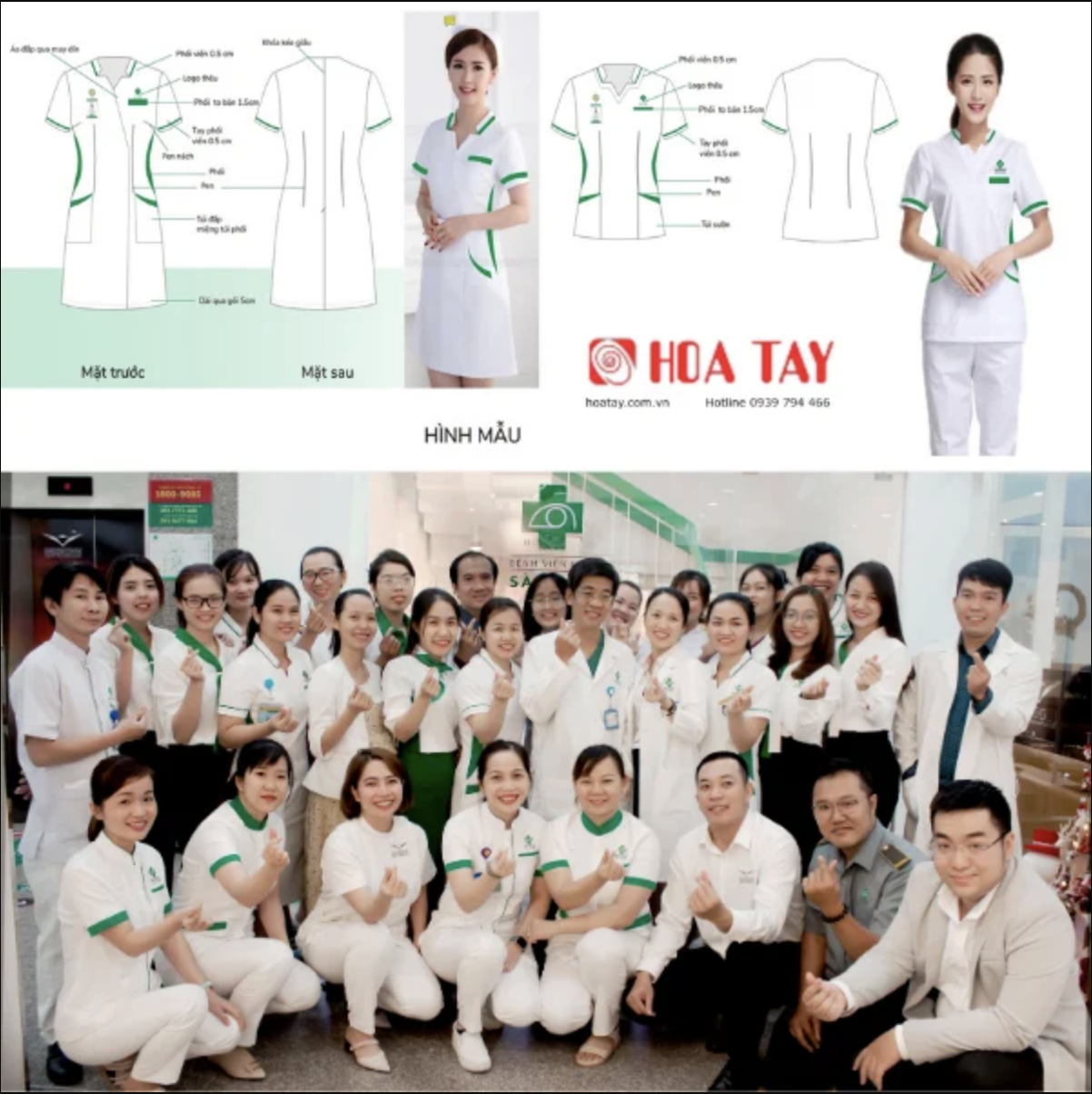
Nguyên tắc chung là chọn font có khoảng chữ hẹp (narrow tracking) và thân chữ mảnh (light weight) cho các chức danh dài. Cách tiếp cận này đảm bảo mỗi nét thêu có đủ diện tích vải để bám dính, tránh tình trạng chỉ bị căng đứt hoặc lem nhòe. Sự gọn gàng của font chữ chính là yếu tố then chốt giúp giữ nguyên tính chuyên nghiệp của bộ đồng phục y tế.
So sánh kỹ thuật thêu đồng phục giữa 3 nhóm font chữ
Khi đối mặt với các chuỗi ký tự dài như “PGS.TS” hay “BS.CKII”, việc lựa chọn font chữ là bài toán kỹ thuật trực tiếp. Mỗi nhóm font tương tác khác nhau với mũi chỉ và vải, ảnh hưởng đến độ rõ nét của chữ sau thời gian sử dụng.
Nhóm font in đậm và Serif
Nhóm này mang lại cảm giác trang trọng, phù hợp với không khí y tế. Tuy nhiên, thân chữ dày khiến chúng chiếm nhiều không gian ngang hơn. Khi áp dụng cho chức danh dài, mật độ mũi thêu phải dày hơn để đảm bảo độ phủ, dễ dẫn đến tình trạng các nét chữ bị lem nhòe. Nếu kích thước chữ bị thu nhỏ, các chân serif mảnh sẽ dễ bị đứt gãy hoặc biến dạng trong quá trình vận hành máy.
Giới hạn của font viết tay
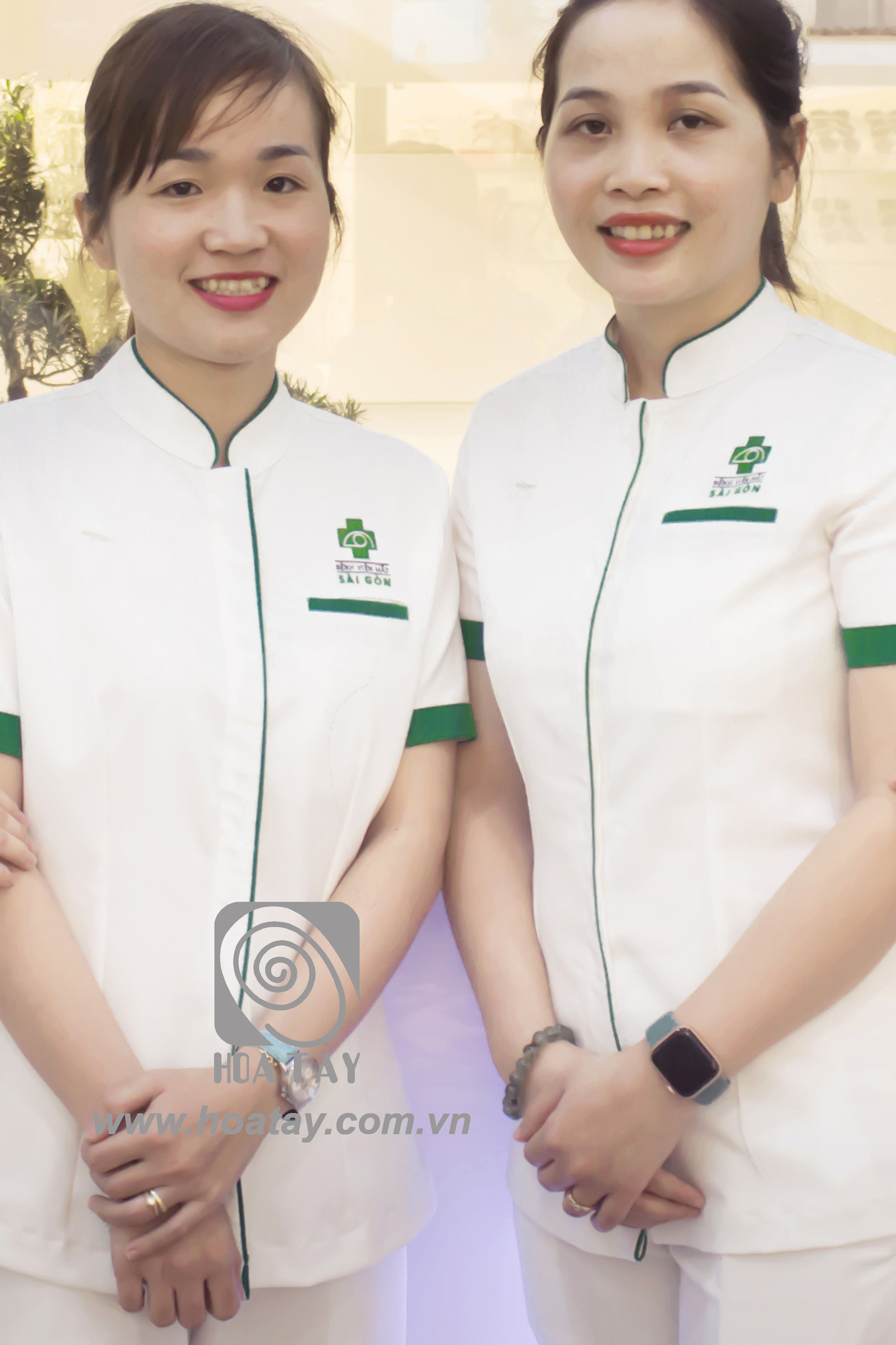
Font viết tay (calligraphic) tạo vẻ mềm mại và nghệ thuật, phù hợp cho tên ngắn. Tuy nhiên, khi thêu tên y bác sĩ có học vị dài, các nét uốn lượn tạo ra nhiều điểm chuyển hướng cho kim thêu. Điều này đòi hỏi tay nghề cao để tránh chỉ bị đứt đoạn. Với chuỗi ký tự dài, font viết tay thường tạo cảm giác rối rắm và khó đọc từ xa, làm giảm tính chuyên nghiệp trong môi trường bệnh viện.
Giải pháp tối ưu: Sans-serif medium weight
Nhóm font không chân (sans-serif) với độ dày vừa phải (medium weight) được xem là lựa chọn an toàn nhất. Chúng cân bằng tốt giữa tính hiện đại và độ bền. Cấu trúc ký tự thẳng và đồng đều giúp máy thêu duy trì mật độ mũi ổn định, tránh hiện tượng phồng vải. Font sans-serif medium weight giúp chữ thêu sắc nét, dễ đọc ngay cả ở kích thước nhỏ, đồng thời giữ được sự trang trọng mà không quá nặng nề như font serif.
Vị trí thêu tên y bác sĩ: nguyên tắc không che bảng tên
Xác định đúng vị trí là bước quyết định để bộ đồng phục vừa đạt thẩm mỹ vừa không cản trở công việc. Quy tắc chung trong kỹ thuật thêu đồng phục là đặt chuỗi ký tự ở ngực trái hoặc tay áo trái. Yếu tố then chốt là chữ thêu không được chồng lấp lên logo bệnh viện hay vị trí gắn bảng tên. Điều này giúp người bệnh dễ dàng nhận diện nhân viên mà không cần tách bảng tên ra.
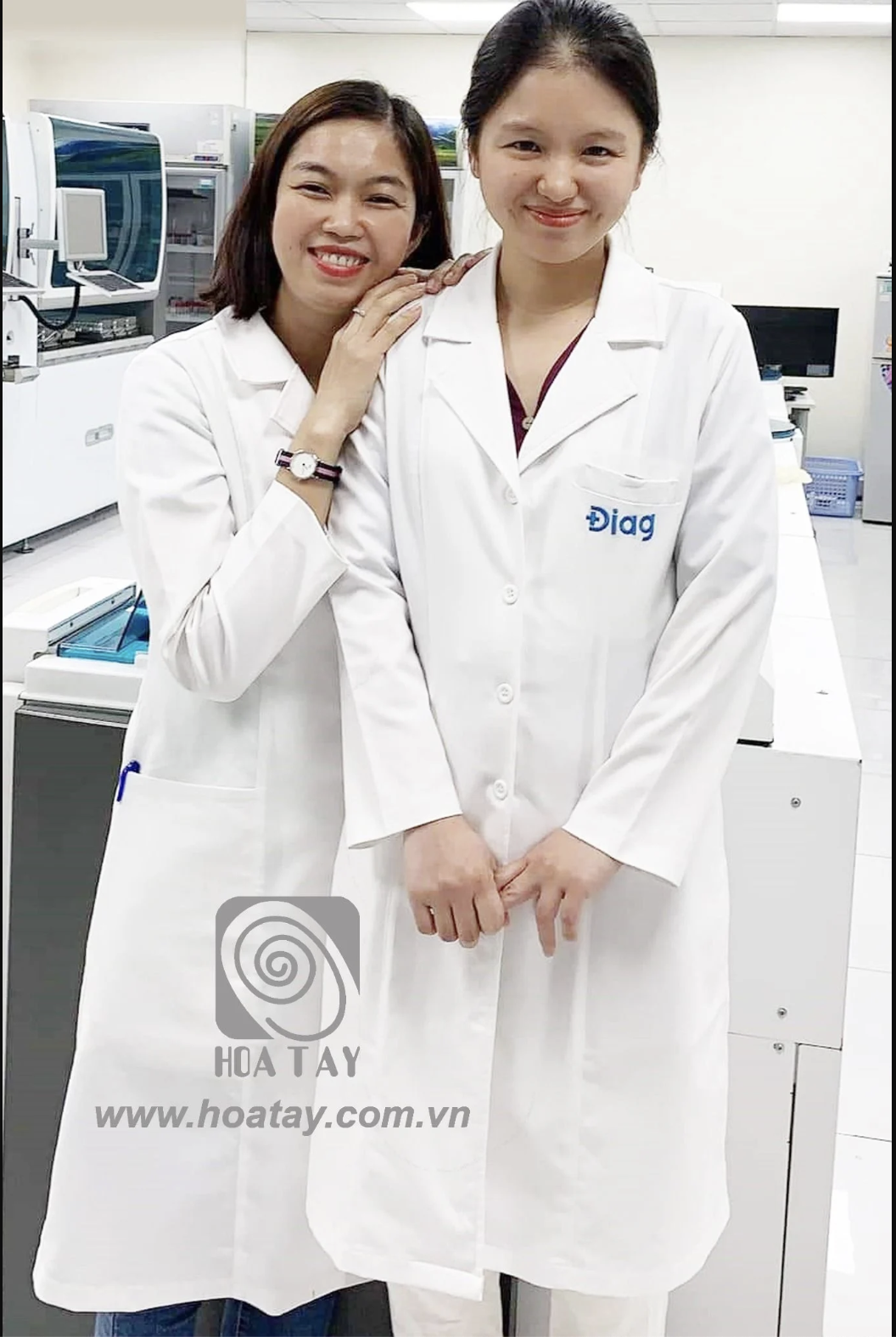
Khoảng cách từ mép áo đến mép chữ thêu cần đủ lớn để hấp thụ sự giãn nở của vải. Khi blouse bị giặt ủi nhiều lần, vải co giãn hoặc xê dịch là điều khó tránh. Nếu đặt chữ quá sát mép, lực kéo này sẽ khiến đường thêu bị biến dạng. Do đó, chừa khoảng an toàn không chỉ là vấn đề thẩm mỹ mà còn là giải pháp kỹ thuật.
Với các chức danh dài, nên căn chữ theo trục thẳng đứng của thân áo thay vì đường cong cổ áo. Việc căn theo đường viền cổ dễ tạo cảm giác “trôi” chữ khi người mặc thay đổi tư thế. Giữ cho chuỗi ký tự thẳng hàng giúp tổng thể trông gọn gàng và trang trọng hơn, đặc biệt khi sử dụng font chữ thêu đẹp trên nền vải sáng màu.
Tầm quan trọng của độ cân đối khi thêu chữ chức danh
Mỗi loại vải cotton hay polyester phản ứng khác nhau với nhiệt độ và lực giặt. Một khoảng cách chuẩn giúp chữ thêu “hít” được khi vải co lại mà không bị đứt chỉ. Đây là chi tiết nhỏ nhưng quyết định lớn đến vẻ ngoài của áo blouse sau nhiều tháng sử dụng.
Kinh nghiệm thực tế khi xử lý chuỗi ký tự dài
Khi làm việc với các học vị dài, độ dài chuỗi ký tự tăng lên đáng kể. Thay vì co giãn chữ, cách hiệu quả hơn là kiểm tra lại vị trí đặt. Nếu vị trí ngực bị “đầy” do logo hoặc bảng tên, việc chuyển lên tay áo là giải pháp thay thế hợp lý. Quan trọng nhất là đảm bảo sự thống nhất giữa toàn bộ nhân viên trên cùng một mẫu áo.
Kỹ thuật thêu: chỉ cotton vs polyester và độ bền đường mũi
Việc chọn loại chỉ thêu quyết định tuổi thọ của đường mũi sau nhiều lần giặt nóng. Chỉ cotton tự nhiên tạo bề mặt mờ, mang vẻ trang trọng phù hợp với áo blouse trắng. Tuy nhiên, khả năng chống phai màu và co rút của cotton thường kém hơn so với polyester. Ngược lại, chỉ polyester cao cấp có độ bóng nhẹ, giúp chữ thêu giữ màu sắc tốt hơn và ít bị biến dạng khi tiếp xúc với nhiệt độ cao.
Đối với các chức danh dài, độ bền của đường mũi là tiêu chí quan trọng. Khi thêu font chữ mảnh, mật độ mũi thêu cần được kiểm soát chính xác. Nếu mũi thêu quá thưa, các nét mảnh dễ bị đứt gẫy. Ngược lại, nếu quá dày, vải tại vùng thêu sẽ bị cứng và phồng lên. Sự cân bằng này đòi hỏi kinh nghiệm thực tế để đảm bảo chữ nổi rõ mà không gây khó chịu khi mặc.